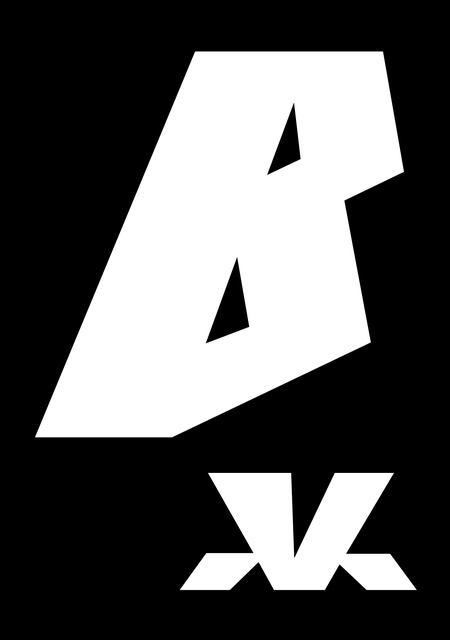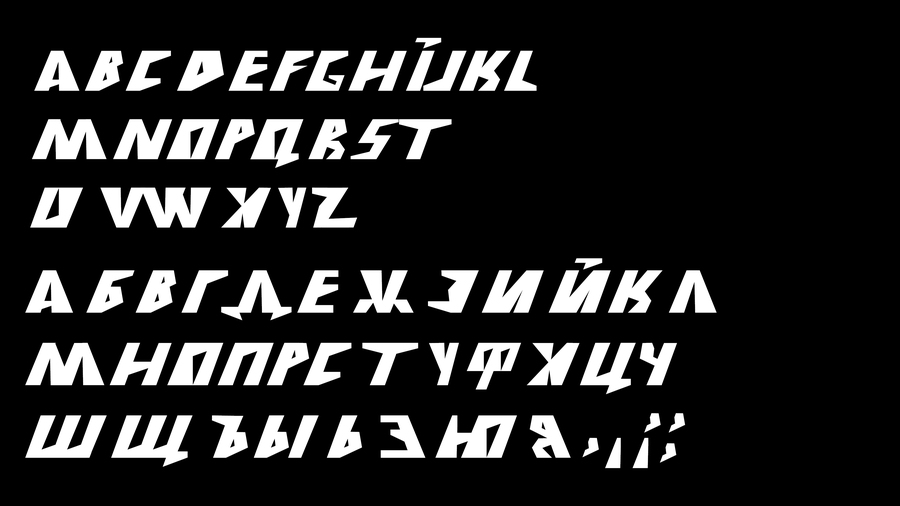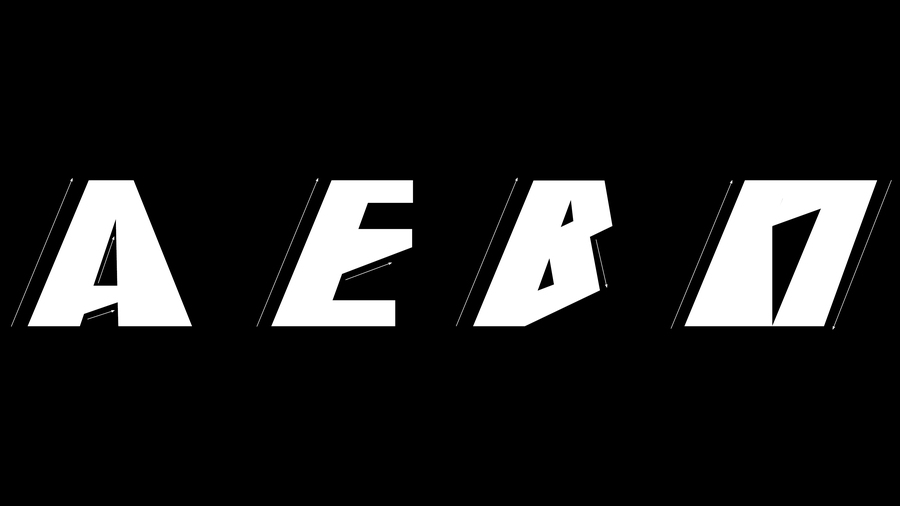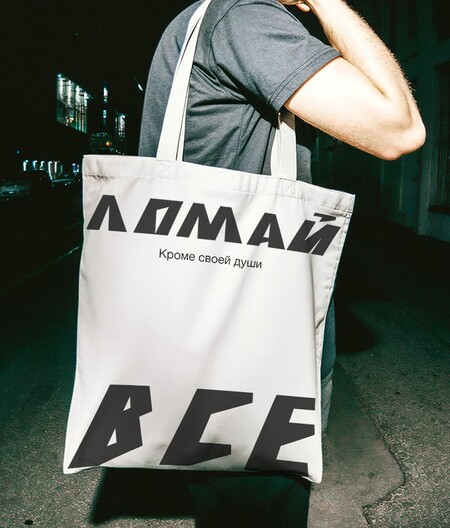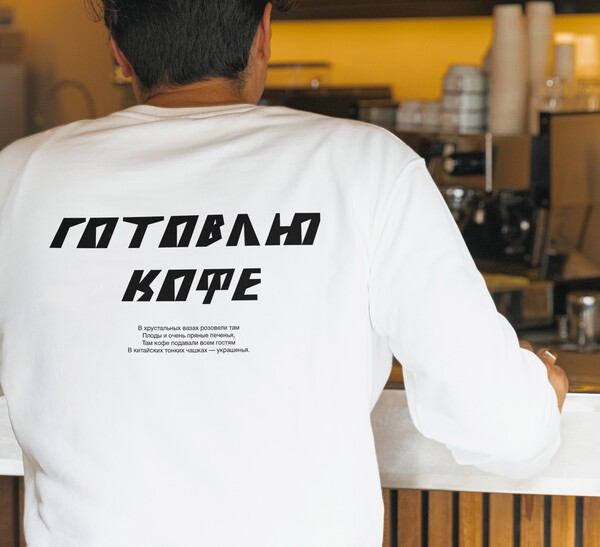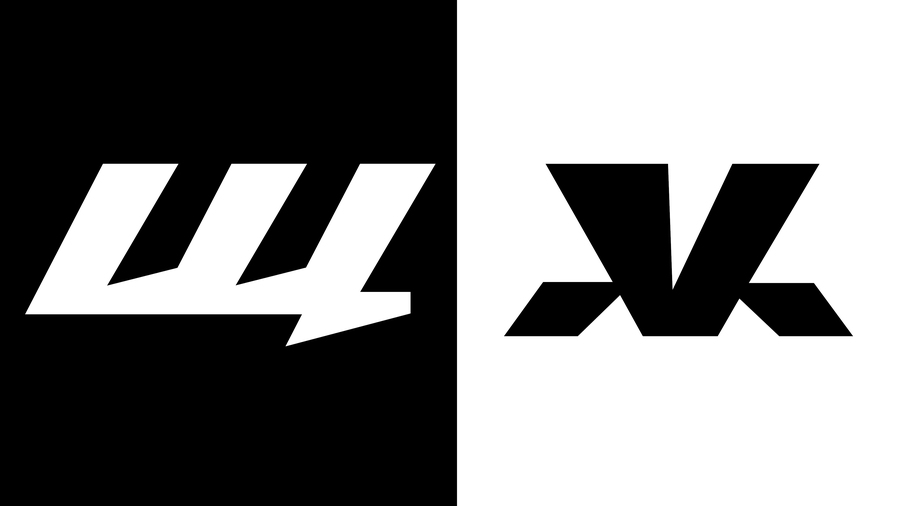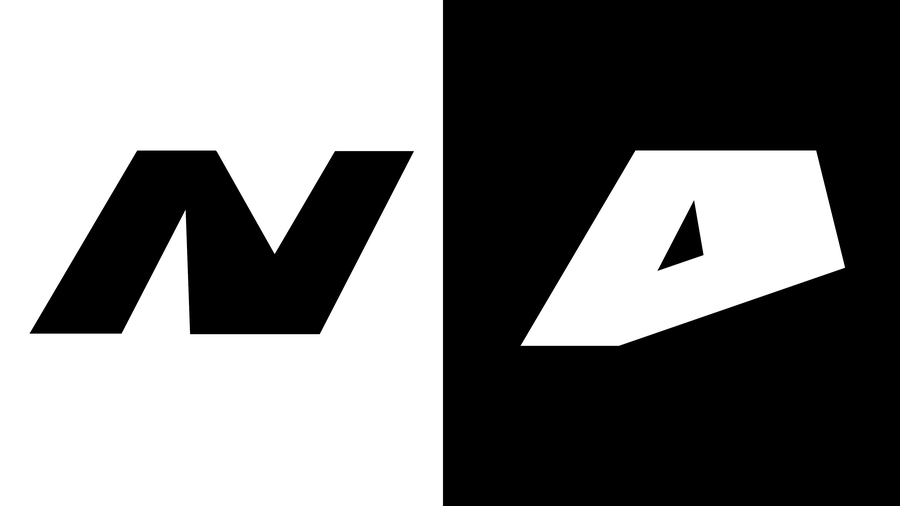
BROKE | шрифт акциденция
Концепция
Шрифт ломает привычные формы, нарушая стандарты типографики. Он отражает состояние неопределённости: старые методы не работают, новые ещё не найдены. Асимметрия, искажённые линии и неожиданные пропорции создают ощущение кризиса и поиска. Такой шрифт — визуальная метафора трансформации, где хаос становится частью нового начала.